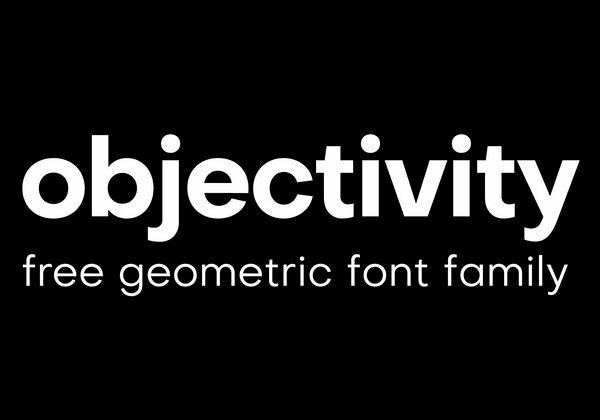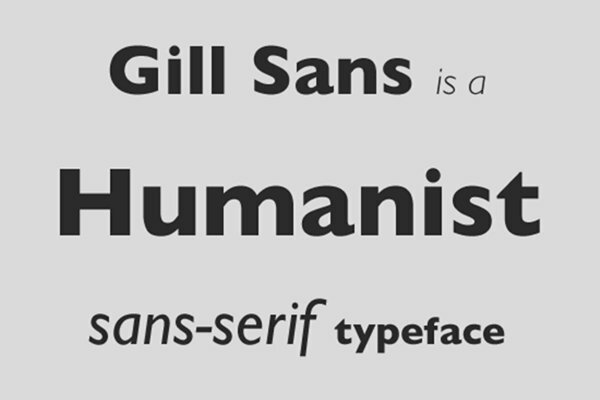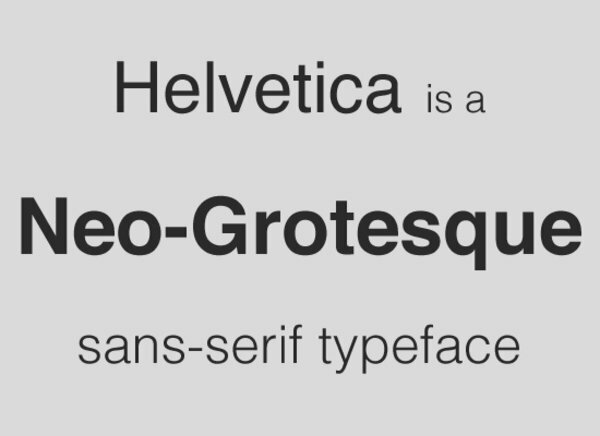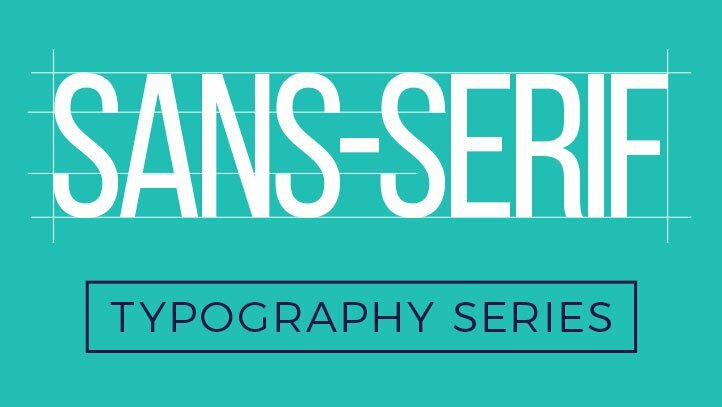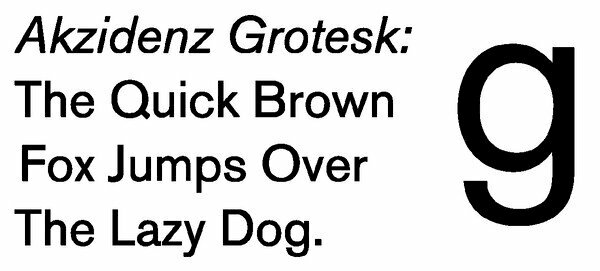
Font sans serif là gì? Đặc điểm và ứng dụng của font sans serif
Font sans serif là gì? Font chữ không chân là gì? Tìm hiểu đặc điểm, ứng dụng và các loại font chữ serif được sử dụng phổ biến nhất hiện nay.
Font sans serif là gì?
Font sans serif là trong tiếng Latin có nghĩa là "không có chân", do vậy sans serif được gọi là font chữ không chân, dùng để chỉ các kiểu chữ không có thêm các yếu tố "serif" như các đường nét nhỏ, đường thẳng trên thành phần chữ.
Đặc điểm của font chữ sans serif
Sau đây là những ưu nhược điểm của font chữ sans Serif
Ưu điểm
Font sans serif có những ưu điểm như sau:
• Dễ đọc trên màn hình: Với các nét chữ rõ ràng và sạch sẽ không có các chi tiết nhỏ và chân, font chữ sans serif thường dễ đọc trên các thiết bị điện tử và màn hình máy tính, phù hợp cho các ấn phẩm online slide thuyết trình, các trang web…
• Hiện đại và thời trang: Font chữ sans serif thường có vẻ ngoài hiện đại và thời thượng, phù hợp với các thiết kế đương đại và trang web.
• Phù hợp cho tiêu đề và chữ số lớn: Vì tính đơn giản và dễ nhìn, font chữ sans serif thường được sử dụng cho các tiêu đề, chữ số lớn và các phần tử nhấn mạnh trong thiết kế.
Nhược điểm
Bên cạnh những ưu điểm thì sans serif còn có những nhược điểm như:
• Khó đọc trong văn bản dài: Đối với các văn bản dài và liên tục, font chữ sans serif có thể không dễ đọc như font chữ serif, vì thiếu các đường kết nối giữa các ký tự.
• Khó phân biệt ký tự: Một số font sans-serif có thể khiến một số ký tự khó phân biệt, chẳng hạn như "l" và "I" (chữ thường "L" và chữ hoa "i").
• Không phù hợp cho ngữ liệu truyền thống: Trong một số tài liệu truyền thống như sách in, các font sans-serif có thể không phù hợp vì không tạo ra cảm giác truyền thống
Các loại font chữ sans-serif
Sau đây là các loại font chữ sans-serif
Grotesque
Hầu hết các kiểu chữ Grotesque đều ra đời cuối thế kỉ 19 - đầu thế kỉ 20. Font chữ sans-serif  này ảnh hưởng bởi kiểu chữ serif Didone và cách vẽ biển hiệu thời đó. Kiểu chữ Grotesque có đặc điểm nổi bật là có thiết kế chắc chắn, thích hợp với các headline hoặc biển quảng cáo. Khoảng cách chiều cao giữa đỉnh các chữ hoa và in thường rất ít  và thường được sử dụng dưới dạng chữ in hoa.
Neo-grotesque
Neo Grotesque
Kiểu chữ Neo-grotesque đã xuất hiện vào những năm 1950 cùng với International Typographic Style (hay được gọi là Swiss Style). Có thể bạn chưa biết Helvetica – typeface được ra đời vào năm 1957 được dùng trong nhiều thập kỷ sau này chính là thuộc dòng neo-grotesque. Font chữ Neo-grotesque có thiết kế đơn giản, thường có các nét thanh đậm khác nhau và dễ dạng sử dụng trong nhiều thể loại văn bản.
Geometric
Kiểu chữ Sans serif Geometric lấy cảm hứng từ các hình khối vuông và tròn. Kiểu chữ này ra đời từ những năm 1920 tại Đức với Herbert Bayer và Jakob Erbar được cho là nhà phát minh của kiểu chữ này. Với thiết kế hiện đại, gọn gàng kiểu chữ này đã trở nên phổ biến vào những năm 20-30 của thế kỷ 20.
Geometric
Geometric có đặc điểm nổi bật là chữ "O" được thiết kế như hình tròn hoàn hảo. Kiểu chữ này thường được sử dụng cho tiêu đề hoặc đoạn văn ngắn, tuy nhiên ít được dùng với các đoạn văn bản dài.
Humanist
Kiểu chữ Sans serif Humanist được thiết kế, cấu tạo đa dạng hơn với những kiểu chữ trước. Một số typeface sẽ có độ tương phản rõ nét, trong khi số khác lại hơi mang hơi hướng Geometric, còn có typeface mô phỏng kiểu dáng của chữ viết tay hoặc thư pháp.
Humanist
Humanist rất phù hợp để sử dụng trên màn hình hoặc ở các khoảng cách xa vì các đặc điểm nổi bật của kiểu chữ này chính là khoảng cách giữa các nét chữ lớn.
Ứng dụng của font chữ Serif
Font chữ sans serif được sử dụng rộng rãi trong nhiều ứng dụng khác nhau. Dưới đây là một số ví dụ về các ứng dụng phổ biến của font chữ sans serif:
Thiết kế trang web và giao diện người dùng (UI)
Font chữ sans serif là lựa chọn hàng đầu của designer khi thiết kế trang web và giao diện người dùng (UI). Vì tính dễ đọc trên màn hình và vẻ ngoài hiện đại, font chữ sans serif giúp cải thiện trải nghiệm người dùng và tạo nét hiện đại cho các giao diện số.
Thiết kế đồ họa
Font chữ sans serif thường được sử dụng trong thiết kế đồ họa, bao gồm thiết kế logo, bộ nhận diện thương hiệu, poster, banner, và các tài liệu quảng cáo. Với vẻ ngoài hiện đại và đơn giản, font chữ sans serif thích hợp để tạo điểm nhấn và thu hút sự chú ý.
Tiêu đề và đầu mục
Các font sans-serif thường được sử dụng cho tiêu đề và đầu mục trong các tài liệu, báo cáo và trang in, giúp tạo ra sự nổi bật và gây ấn tượng.
So sánh phân biệt Serif và Sans-serif
Dưới đây là một bảng so sánh giữa font chữ serif và sans-serif trong các khía cạnh khác nhau:
Tính chất Serif Sans-serif
Cấu trúc Có các chân (serifs) Không có chân
Độ dễ đọc Dễ đọc trên giấy Dễ đọc trên màn hình
Phong cách Truyền thống, chính trị Hiện đại, thân thiện
Sử dụng cho Văn bản dài, sách Giao diện, tiêu đề
Đặc điểm Các chân giúp mắt theo dõi dòng dễ hơn Không có chân giúp tạo sự gọn gàng và hiện đại
Ưu điểm Thích hợp cho văn bản truyền thống, cảm giác nghiêm trang Dễ đọc trên màn hình, giao diện hiện đại
Ví dụ font chữ Times New Roman, Georgia Arial, Helvetica, Open Sans